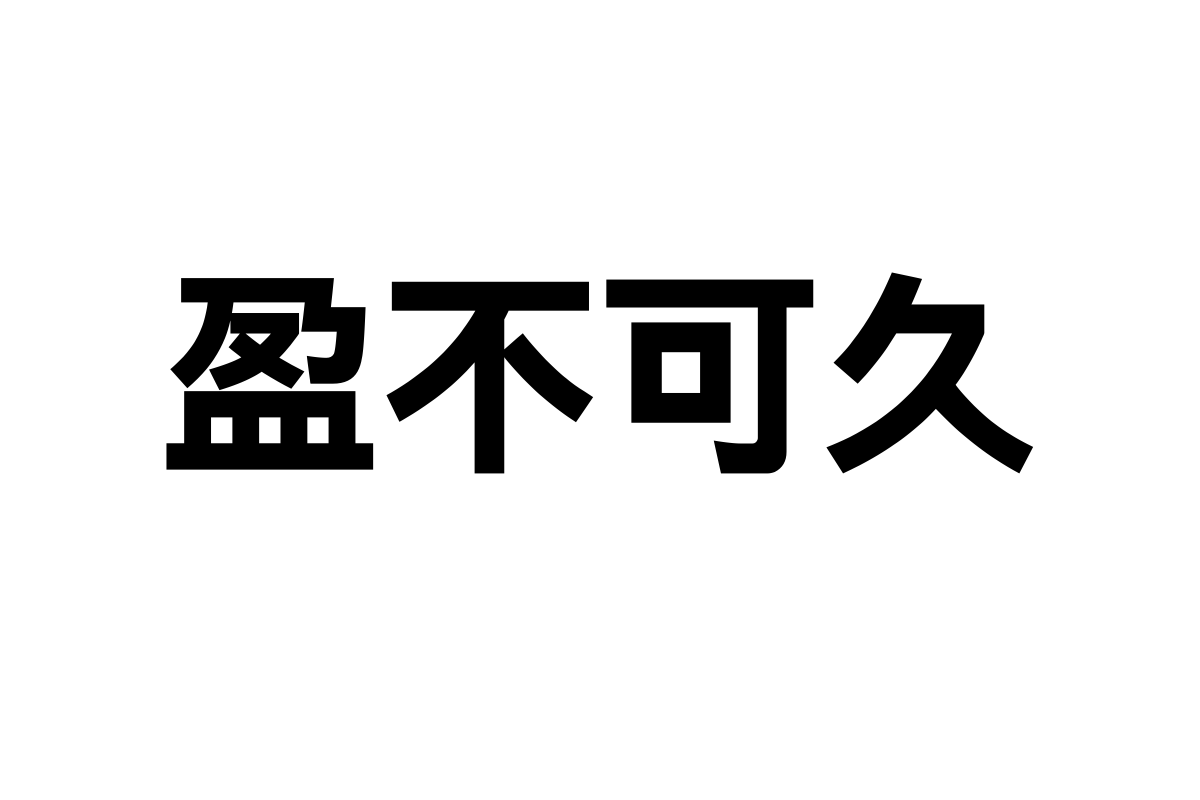
上首简黑粗体是一种中文字体,主要用于印刷和排版。它的设计灵感来源于传统的书法艺术,具有独特的风格和韵味。上首简黑粗体的笔画粗细适中,线条流畅有力,给人一种古朴典雅的感觉。
这种字体的特点是字形结构紧凑,笔画分布均匀,易于阅读和识别。同时,上首简黑粗体的字体大小、字间距和行距都可以调整,可以根据不同的需求进行灵活运用。
上首简黑粗体适用于各种印刷品,如报纸、杂志、书籍等,也常用于网页设计和平面设计中。它不仅具有较高的辨识度,还能增加作品的视觉冲击力,使得文字更加生动有趣。